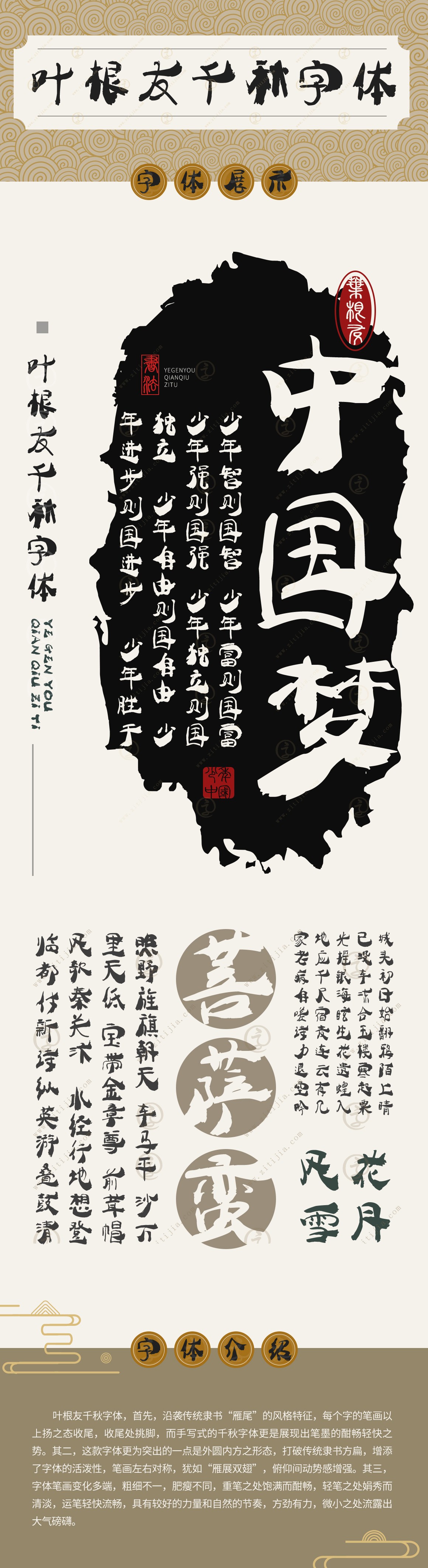
葉根友千秋字體
字體作者:葉根友
創(chuàng)作年代:2013年
字體字數(shù):6763個中文漢字以及其他英文字母和阿拉伯數(shù)字
字體介紹
葉根友千秋字體風格渾厚大氣,延續(xù)隸書的風格特征進行創(chuàng)作,靈感來自韓國電視劇《千秋太后》之劇名書法“后”的風格,經(jīng)過創(chuàng)意改變思維模式,創(chuàng)新了一款葉根友千秋字體作品,這個字體的風格特征是每個字的筆畫尾部都上揚,渾厚而富有書法韻味,濃重之中展現(xiàn)了中國書法抑揚頓挫之運筆追求,是繼蠶燕隸書之后又一毛筆隸書作品的發(fā)布。
創(chuàng)意來源